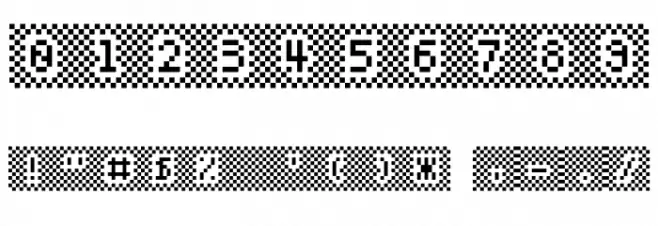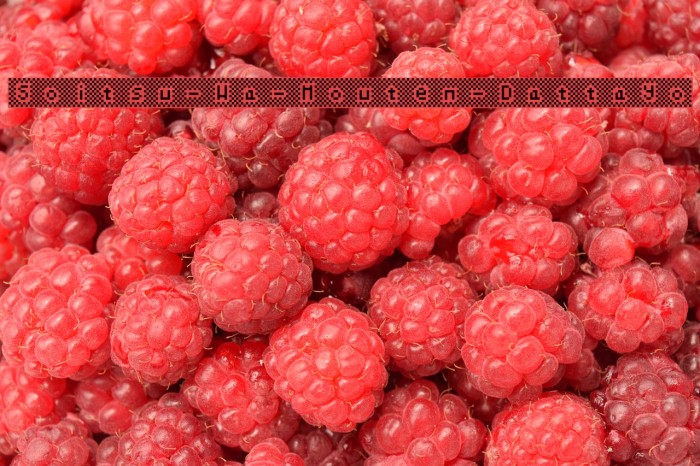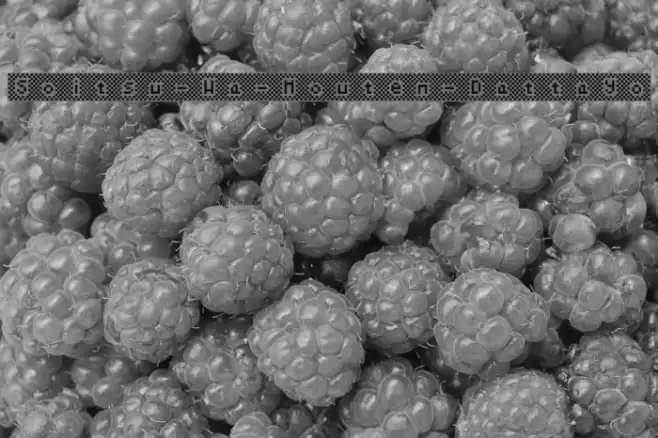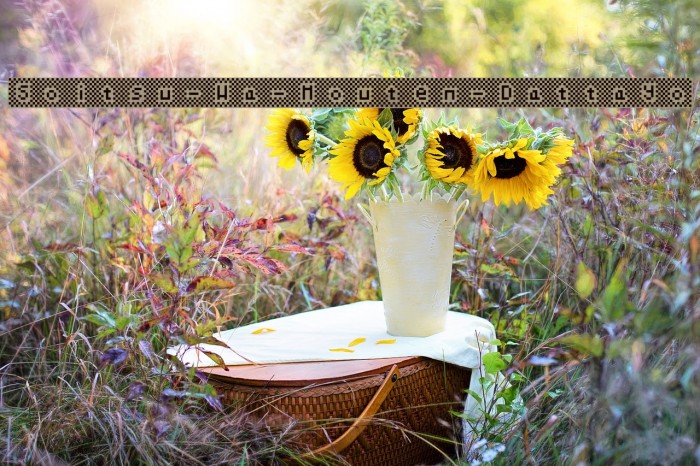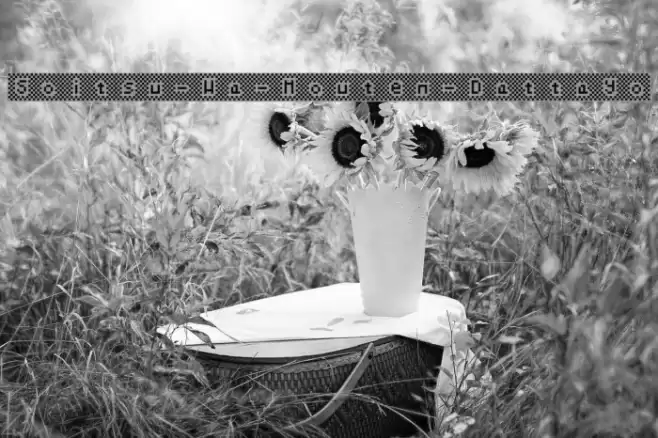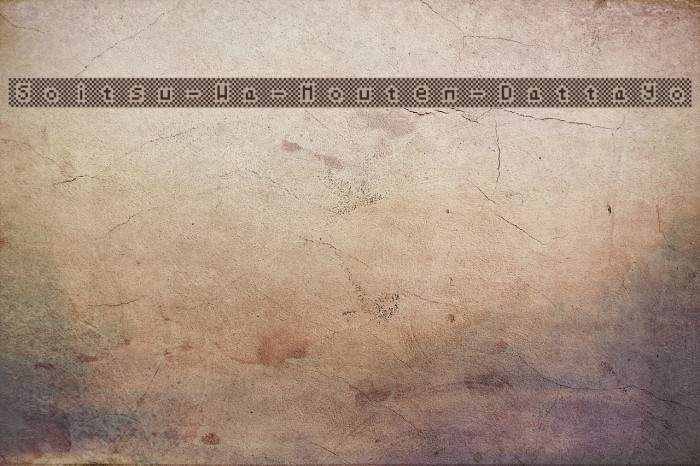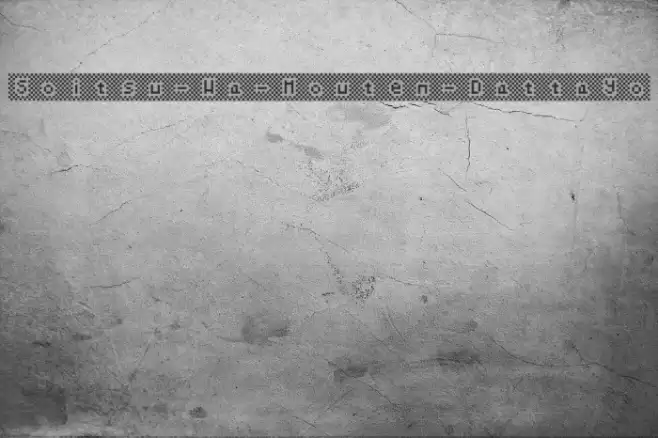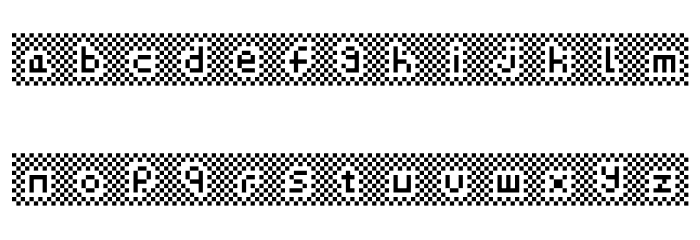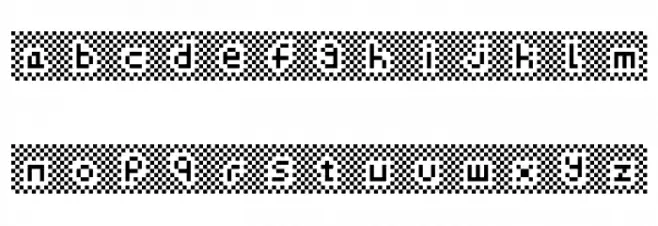
Soitsu-Wa-Mouten-Dattayo Font
✎ Pixel
| Kategorien | Pixel |
| Gesamtstil | Vintage |
| Anwendungsfall | Logos, Headlines, Digital Art |
| Vorgeschlagene Projekte | Ideal for retro video game designs, digital art projects, tech-themed posters, and any creative work that seeks to capture a vintage digital aesthetic. |